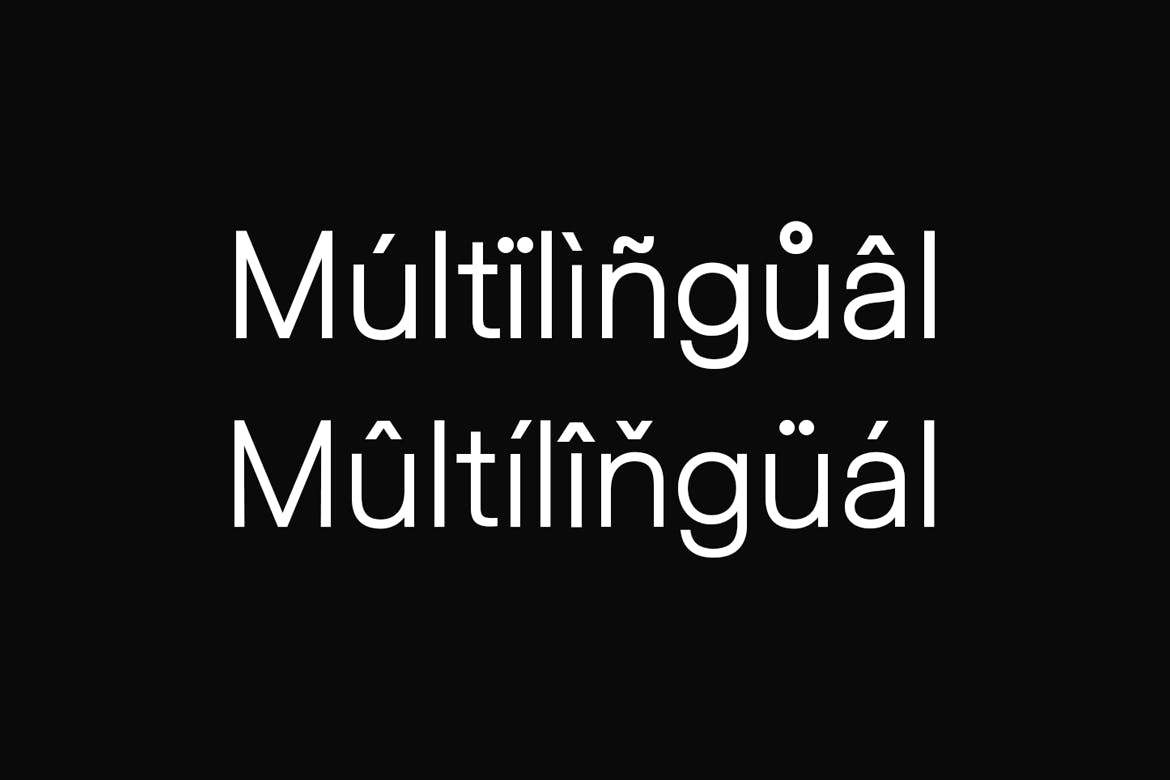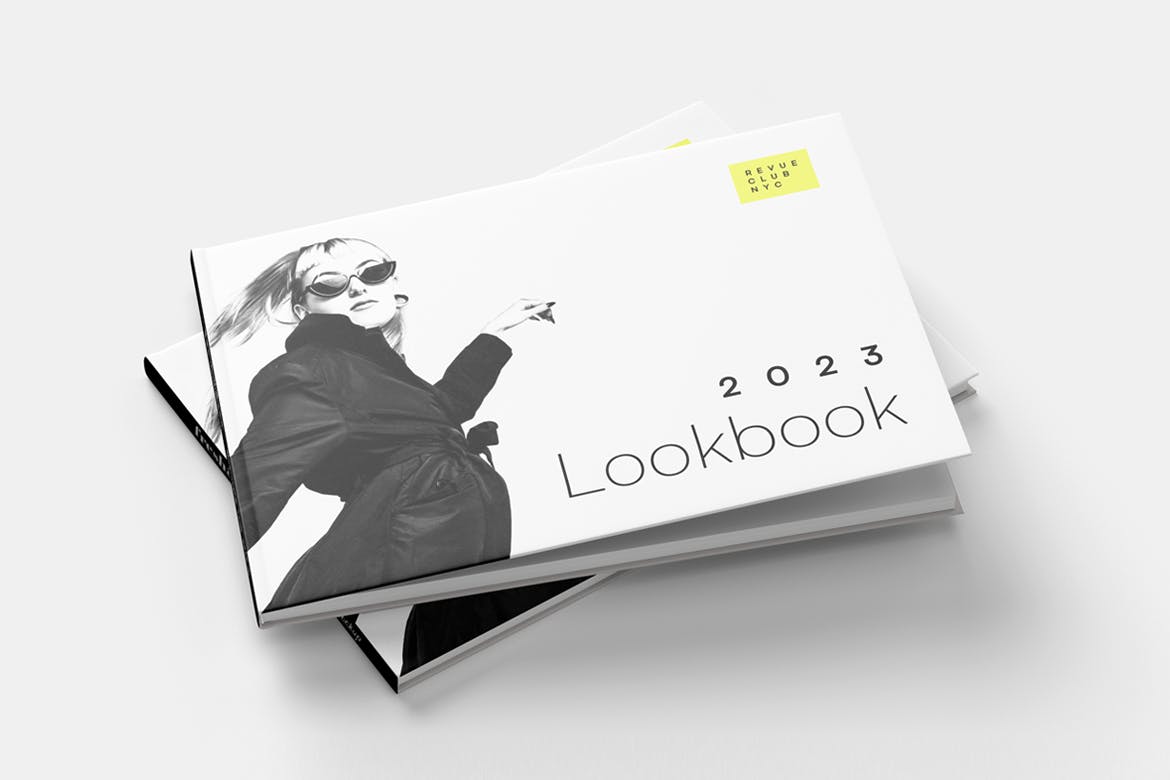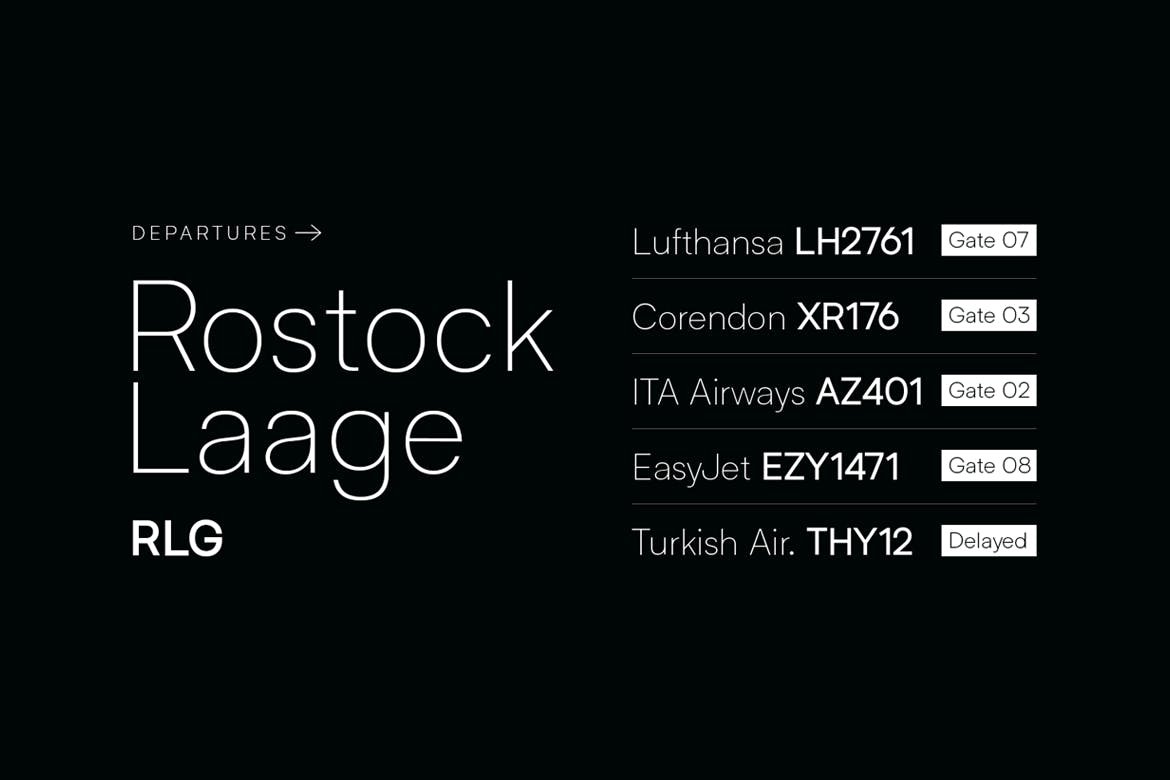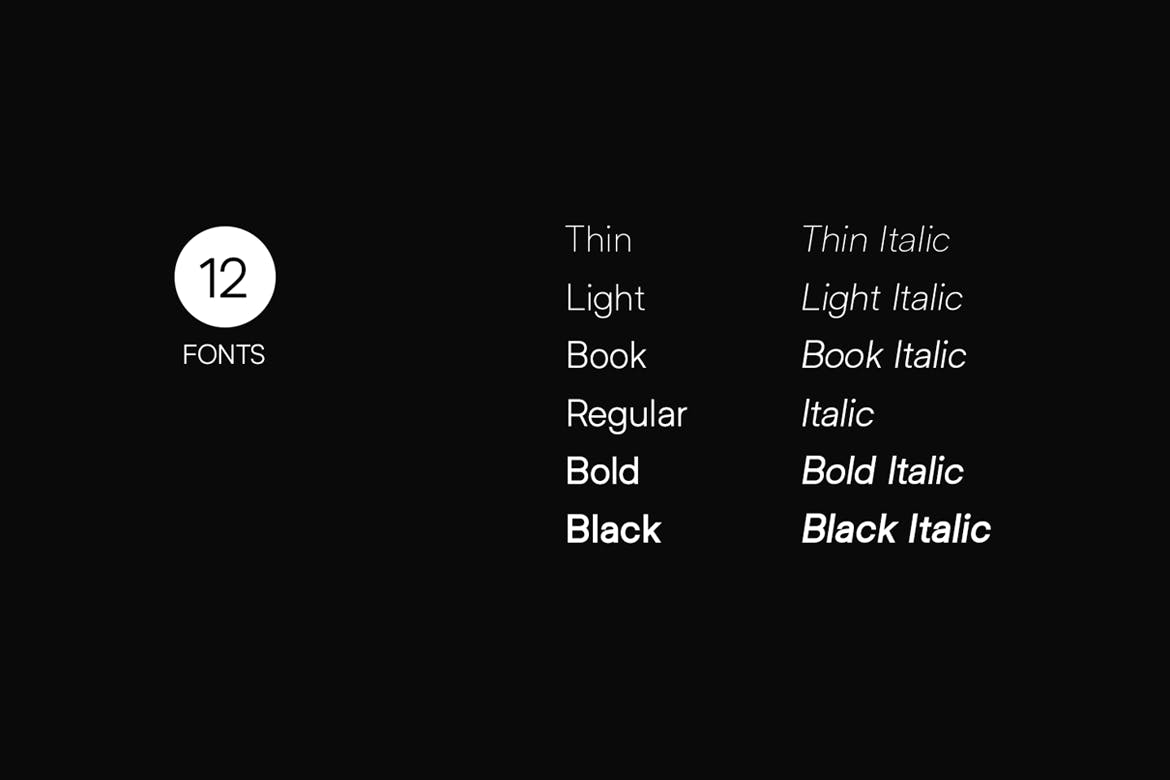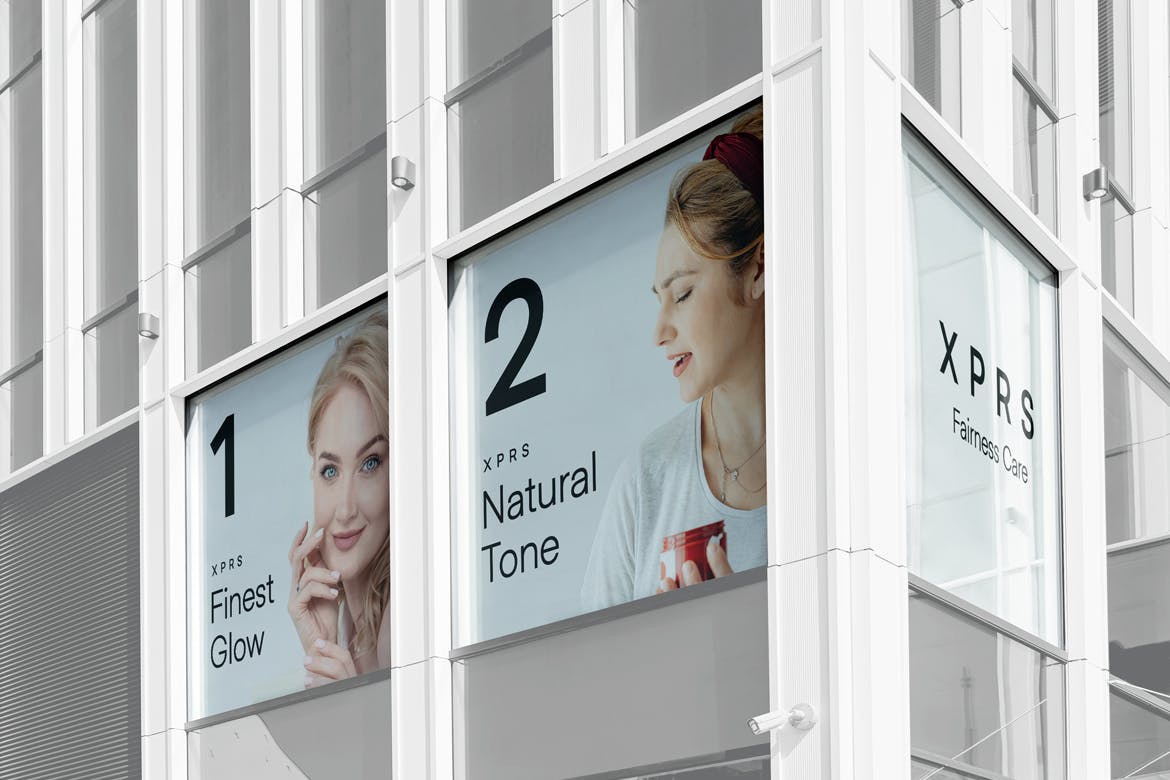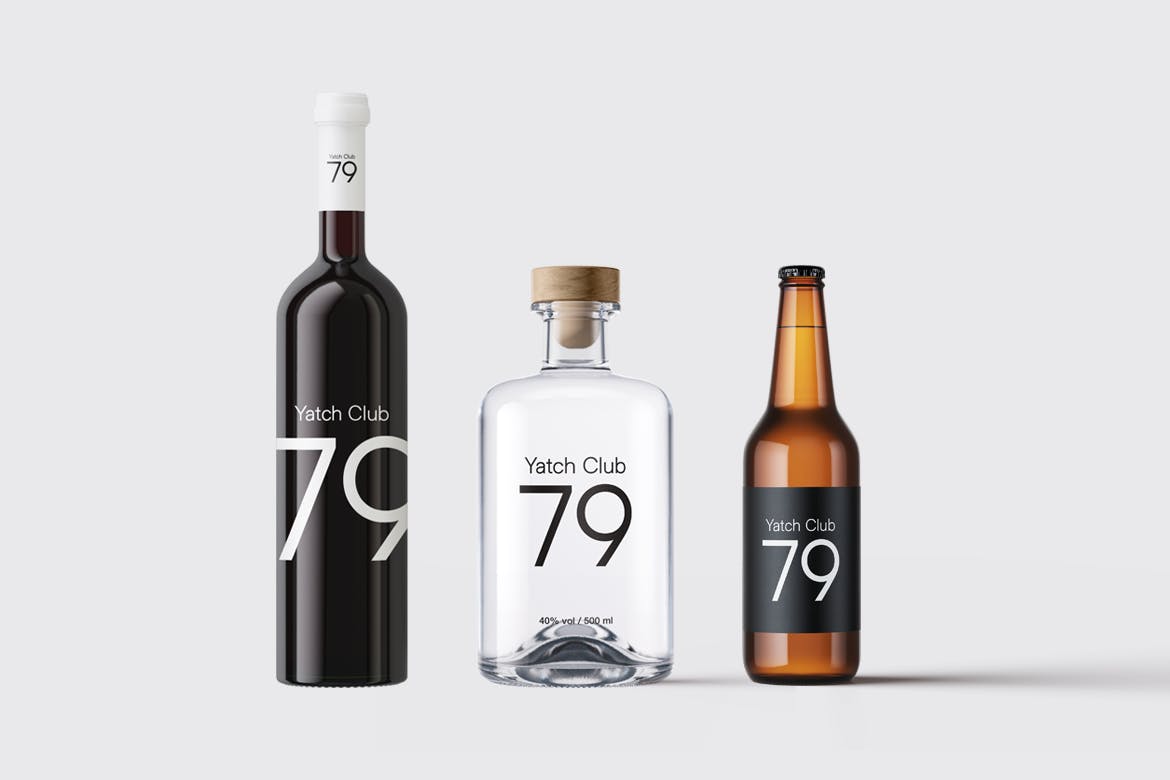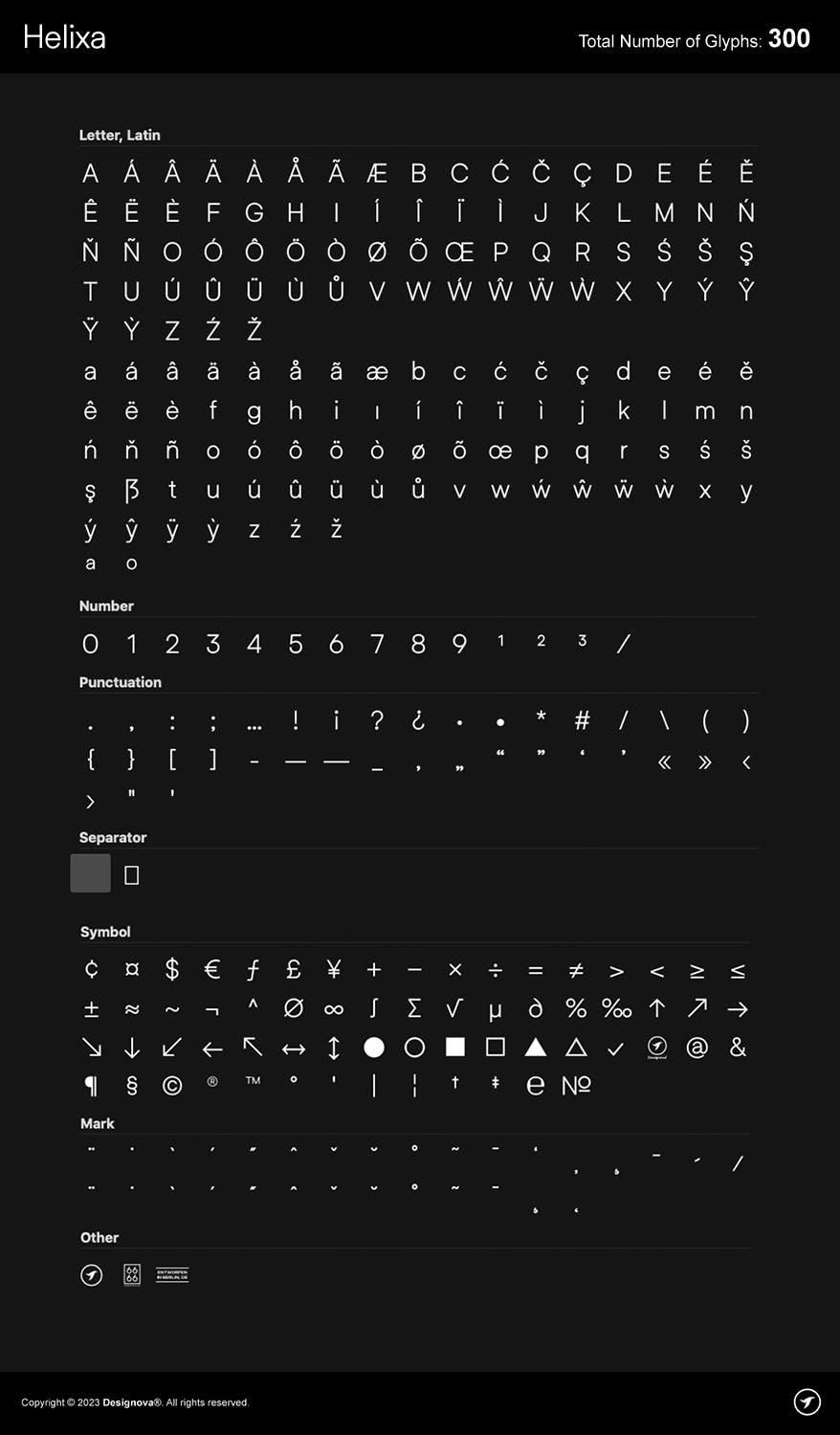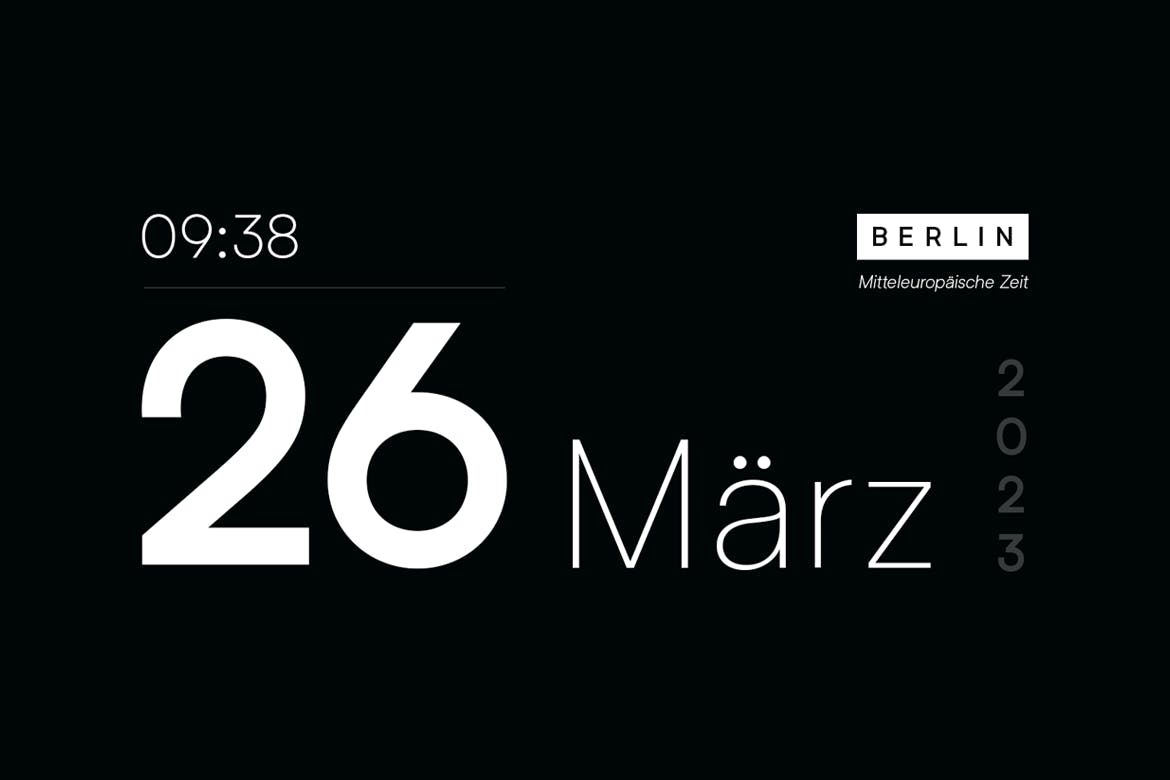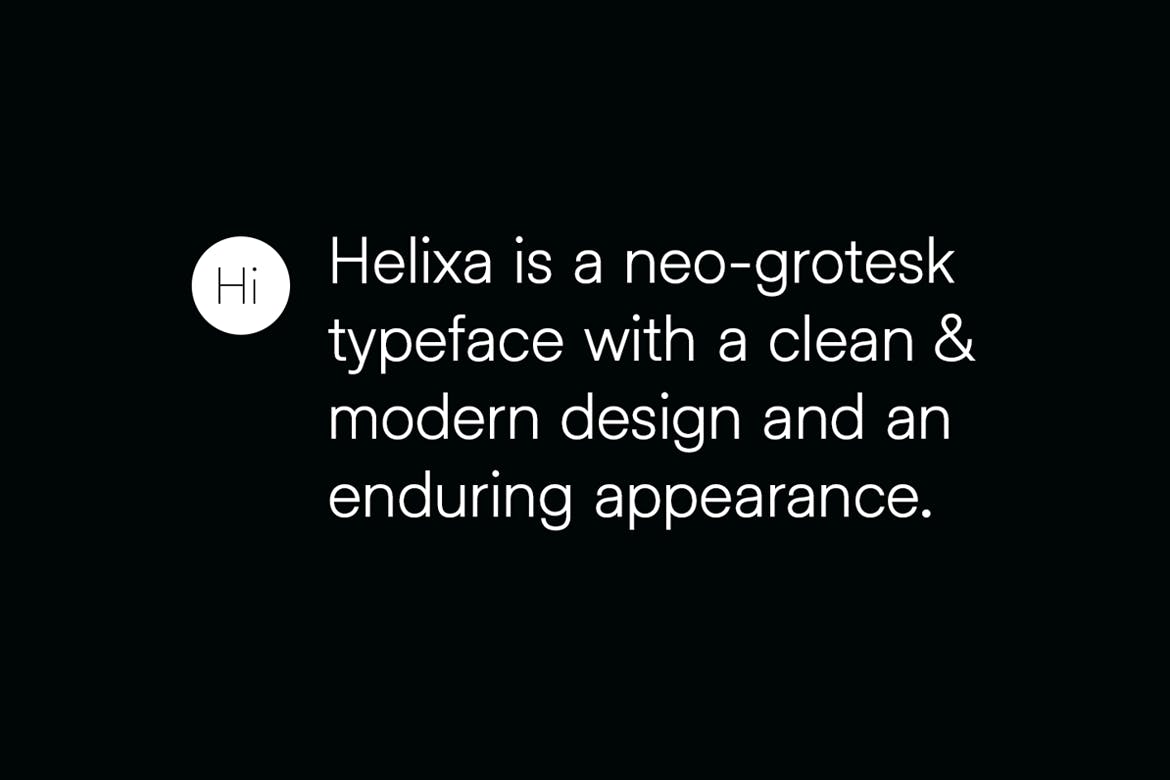
فونت Helixa یک نوع فونت نئوگروتسک با طراحی مدرن و تمیز است که ظاهری ماندگار دارد. این فونت انتخابی عالی برای ایجاد لوگو، برندینگ، عنوانها، هویتهای شرکتی و مواد بازاریابی برای رسانههای وب، دیجیتال و چاپی است.
این فونت گزینهای عالی برای پروژههای طراحی برندینگ، طراحی لوگو/لوگوتایپ، گرافیکهای بازاریابی، بنرها، پوسترها، تابلوها، هویتهای شرکتی و طراحیهای ویرایشی خواهد بود. اضافه کردن فاصله بین حروف، این فونت را به انتخابی مناسب برای عناوین مینیمالیستی و لوگوها تبدیل میکند، همانطور که در طراحیهای تبلیغاتی پیوست شده نشان داده شده است.
این فونت با ویژگیهای قدرتمند OpenType طراحی و ساخته شده است و هر وزن شامل پشتیبانی از زبانهای مختلف با مجموعههای زبانهای اروپای غربی، اروپای مرکزی و اروپای شرقی است. در مجموع 300 گلیف در دسترس است.
فونت Helixa شامل 12 فونت در کل است که شامل هفت وزن ایستاده (Thin / Light / Book / Regular / Bold / Heavy) و معادلهای ایتالیک از شش وزن است. بسته شامل فونتهای دسکتاپ (OTF، TTF) و فونتهای وب (شامل تمامی EOT، SVG و WOFF) است. پیشتنظیم HTML و CSS WebFont و دموی آن در بسته دانلود موجود است.